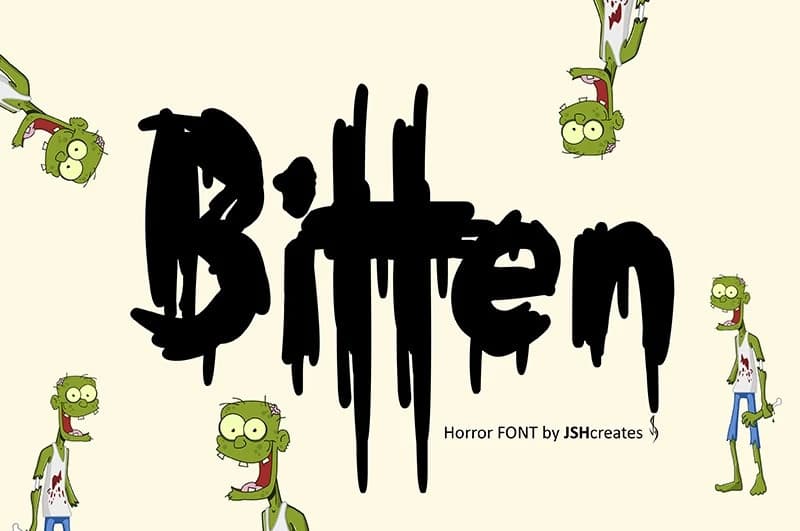
Bitten Horror Font
Bitten Horror Font, damlayan bir korku fontudur; karanlık, ürkütücü enerjiyle yayılan ve ürkütücü bir görsel etki sunan bir tasarıma sahiptir. Keskin, sıvı benzeri harf biçimleri, cesur reklam ve sergileme kullanımları için mükemmeldir; bannerlar, kapaklar, tişörtler, afişler, logolar ve daha fazlas
Bitten Horror Font, karanlık, ürkütücü enerji yayan ve ürkütücü bir görsel etki sunan damlayan bir korku yazı tipidir. Sivri, sıvı benzeri harf biçimleri, kalın reklam ve sergileme kullanımları için mükemmeldir; bannerlar, kapaklar, tişörtler, afişler, logolar ve daha fazlasını içerir.